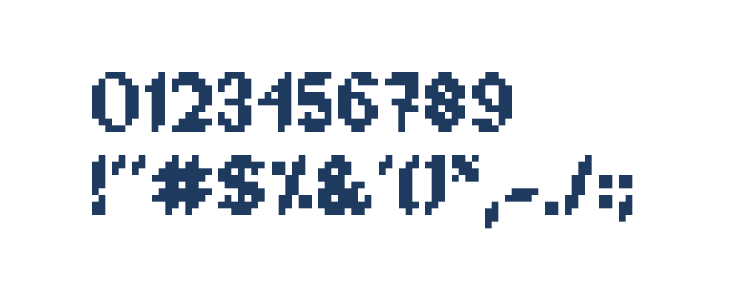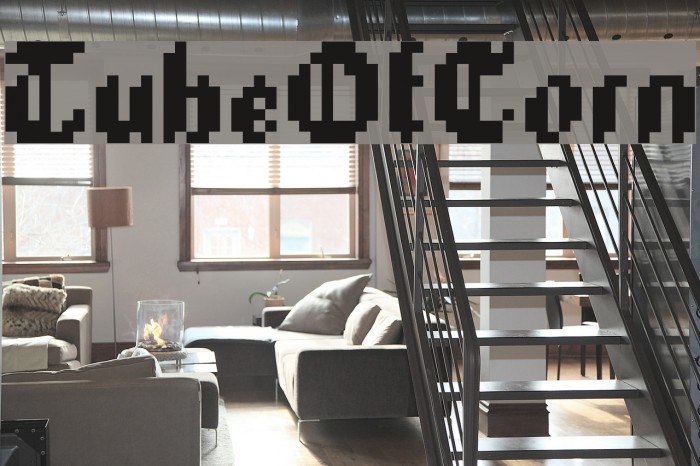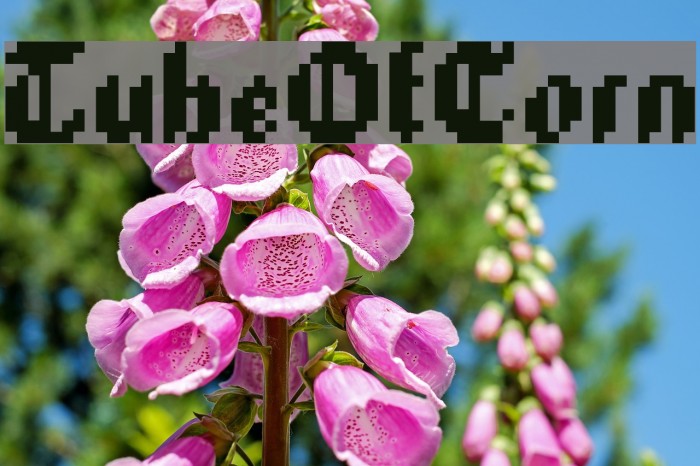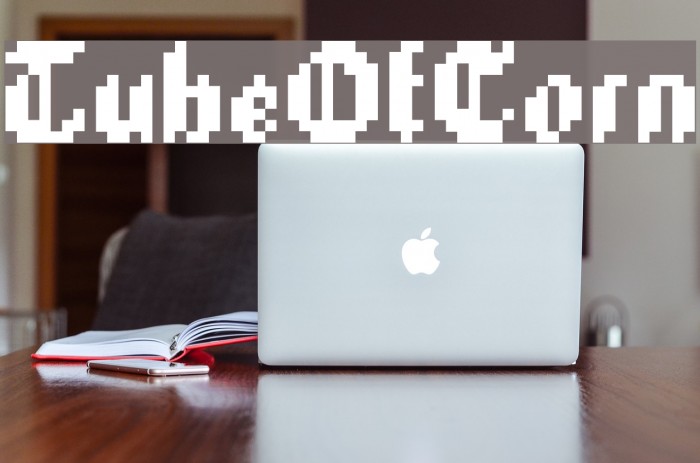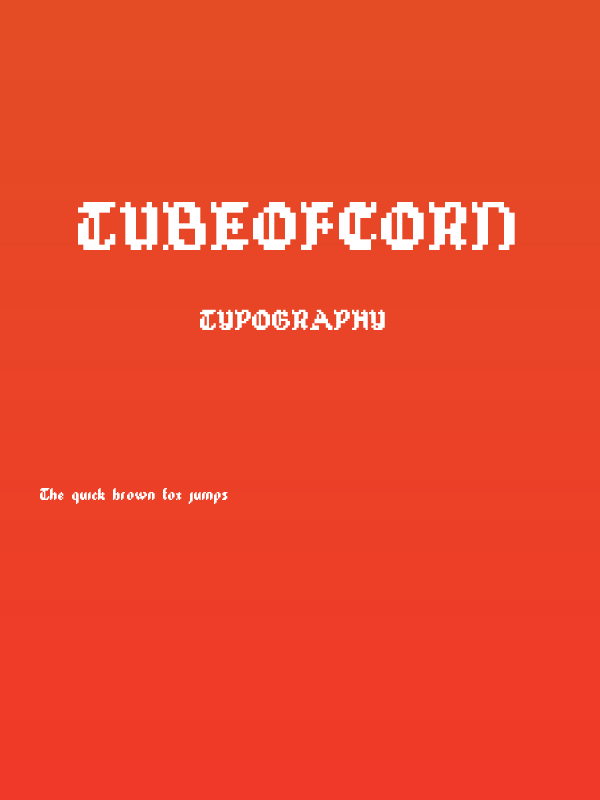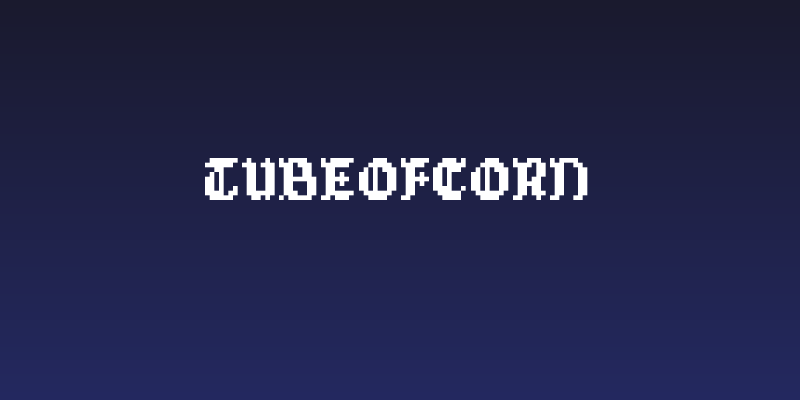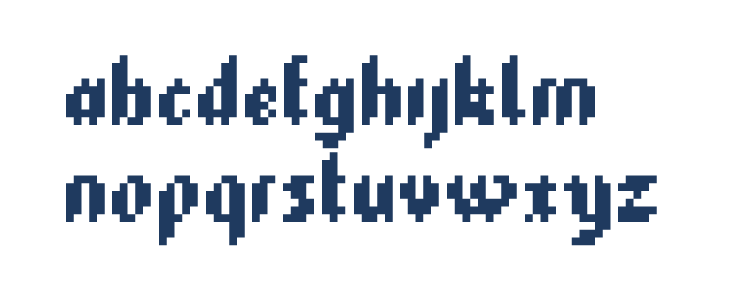
TubeOfCorn Font
Hazel Abbiati - diamondidiocy.tumblr.com
| Gesamtstil | Retro, Digital |
| Vorgeschlagene Projekte | Ideal for video game design, retro-themed posters, digital art, and branding that requires a nostalgic touch. |